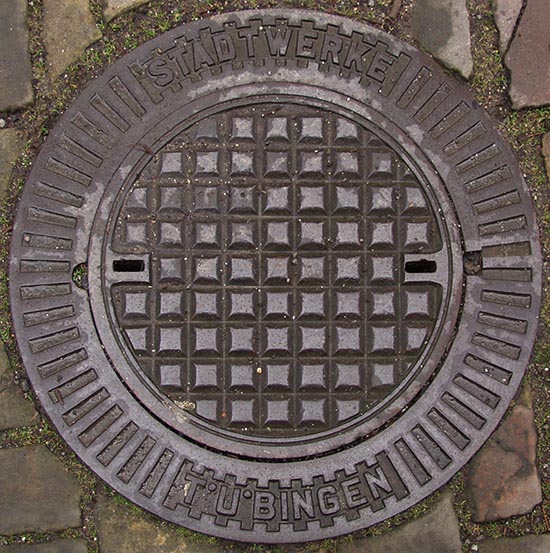
Food for Thought: Ich find’s ja immer seltsam, dass in jedem Typo-Buch steht, dass »Typografie eine dem Leser dienende Kunst ist« – wenn dann aber Fraktur benutzt werden soll, solle man doch auf den Leser pfeifen und zwanghaft einer nicht mehr existenten Tradition folgen … Ist doch die Dummheit des Lesers, wenn der MUFEUM liest!
(Dass das Beispiel oben handwerklich schlecht gemacht war ist natürlich keine Frage. Die offensichtlichen Gründe wurden ja auch schon dargelegt.)
Klar, Deinen Einwand kann ich nachvollziehen. Andererseits: Niemand ist gezwungen, eine gebrochene Schrift einzusetzen – es gibt schließlich unzählige andere Schriften, mit deren Verwendung sich diese Problematik der schwierigen Lesbarkeit umgehen ließe. Und es gibt, wenn ich das aus den Posts hier im Thread richtig herausgelesen habe, auch gebrochene Schriften, die durchaus in ihrer Lesbarkeit behutsam an die gewohnten Formen heutiger Schriften angepasst wurden und sich daher für eine Verwendung in der oben gezeigten Anzeige besser geeignet hätten. Unschön finde ich, wenn Zeichen einer Schrift in einer Weise modifiziert werden, durch die der stimmige formale Gesamteindruck der Schrift beschädigt wird. Und dass das bei dieser Anzeige passiert ist, sieht man ja daran, dass das besprochene Beispiel hier an dieser Stelle eingestellt wurde. Auch klar ist wohl, dass das dem gemeinen Zeitschriftenleser nicht groß auffallen wird, alleine schon deswegen, weil er wohl kaum lange genug seinen Blick auf der Anzeige verweilen lassen wird. ;-)
Ich find’s ja immer seltsam, dass in jedem Typo-Buch steht, dass »Typografie eine dem Leser dienende Kunst ist« – wenn dann aber Fraktur benutzt werden soll, solle man doch auf den Leser pfeifen …
Hier wäre zu unterscheiden zwischen einem Dienst am Leser und einer billigen Anbiederung an den Leser. Dienen im Sinne eines Butlers — ja; im Sinne eines Strichers — nein.
F Ist doch die Dummheit des Lesers, wenn der MUFEUM liest!
So ist es. Und es ist Bestandteil eines vernünftigen Dienens, solche Stolpersteine nicht wegzuräumen. Der mündige Leser wächst ja gerade daran, daß er sich von seinen Wissenslücken herausfordern läßt. Dem Rest wird man auch durch Senkung des Niveaus nicht helfen. Wenn man das Niveau jedes mal senkt, wenn es für eine Bevölkerungsgruppe zur Herausforderung wird, steuert man in logischer Konsequenz die Teletubby-Ebene an.
Mickymaustypografie
Sei froh, daß der Minimalist nicht da ist, der hätte sofort das Schwert zur Verteidigung der Ehre der Maus ergriffen. ;-)
Auch klar ist wohl, dass das dem gemeinen Zeitschriftenleser nicht groß auffallen wird, alleine schon deswegen, weil er wohl kaum lange genug seinen Blick auf der Anzeige verweilen lassen wird. ;-)
… bzw., wofern männlich, den Blick möglicherweise mehr auf die linke Seite konzentriert.
sind eben
Herausforderungen des Lehrerberufs
(Siehe genannte Quelle)
Lehrer werden in Sachsen. Aha. Was werden Lehrer in Sachsen?
gesucht
beworben
in Anzeigen veräppelt
usw.
was auch immer gemeint ist, lehrer sind hier anscheind dringend nötig. :neenee:
würde mich mal interessieren wer sowas verzapft. dumme webdesigner, die nebenbei
banner erstellen? lehrer die nebenbei banner erstellen? oder grafiker die keinen sinn
für gestaltung haben?
Formvollendet ... ;-)
Das ist die Visitenkarte eines Restaurants auf einer beliebten spanischen Urlaubsinsel.
Das Essen dort ist phantastisch. Die Typografie hingegen … :-|
Hmm … welche Sorte Weichgetränke man da wohl serviert bekommt ;-)
Bonaqua, Vio, Urbacher, Apollinaris oder Sodentahler?
Ich hab auch noch was gefunden, was nur bedingt mit Schrift zu tun hat:
Leuchtende Bakterien
Forscher erfinden lebende Geheimschrift
Geheime Depeschen gibt es nicht nur bei WikiLeaks: US-Forscher haben eine unsichtbare Tinte aus gentechnisch veränderten Bakterien entwickelt. Die kleinen Geheimnisträger geben ihre Botschaft erst auf Kommando preis - und die Nachrichten sollen sich sogar selbst zerstören können.
Und wer entwirft jetzt die Times Bio Roman, Helvetica Bacterial und Comic Glow?